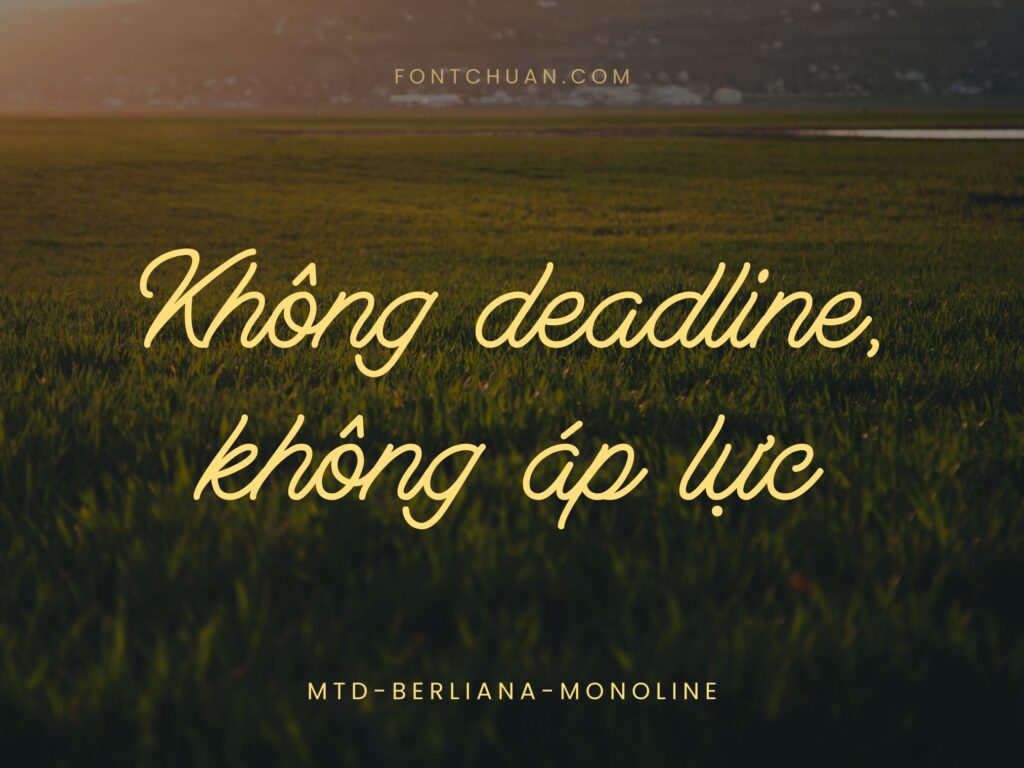
Font MTD Berliana Monoline Việt Hóa
Tác giả Font: Junanobi
Berliana Monoline là một font chữ mang phong cách viết tay tinh tế, được thiết kế bởi Junanobi. Với đặc điểm đường nét mượt mà và liền mạch, font này mang lại sự thanh lịch và hiện đại trong từng ký tự. Để hỗ trợ cộng đồng thiết kế Việt Nam, Mộc Hạ đã Việt hóa Berliana Monoline, giúp font này hỗ trợ đầy đủ tiếng Việt cùng hơn 200 ngôn ngữ khác. Phiên bản Berliana Monoline Việt hóa đã được thành viên Font Chuẩn sưu tầm và đăng tải nhằm mang đến sự lựa chọn phong phú hơn cho các nhà thiết kế.
Về đặc điểm thiết kế, Berliana Monoline sở hữu các đường nét tròn trịa, tạo sự liên kết tự nhiên giữa các ký tự, mang lại cảm giác mềm mại nhưng vẫn đảm bảo tính dễ đọc. Font này rất phù hợp cho các thiết kế thương hiệu, logo, typography nghệ thuật, bao bì sản phẩm và thiệp mời. Ngoài ra, Berliana Monoline cũng là một lựa chọn lý tưởng cho các ngành nghề như quảng cáo, thiệp cưới và giáo dục, giúp mang lại phong cách hiện đại và chuyên nghiệp. Font này cũng rất thích hợp để sử dụng trong các sự kiện như Valentine, Sinh nhật và các lễ hội.